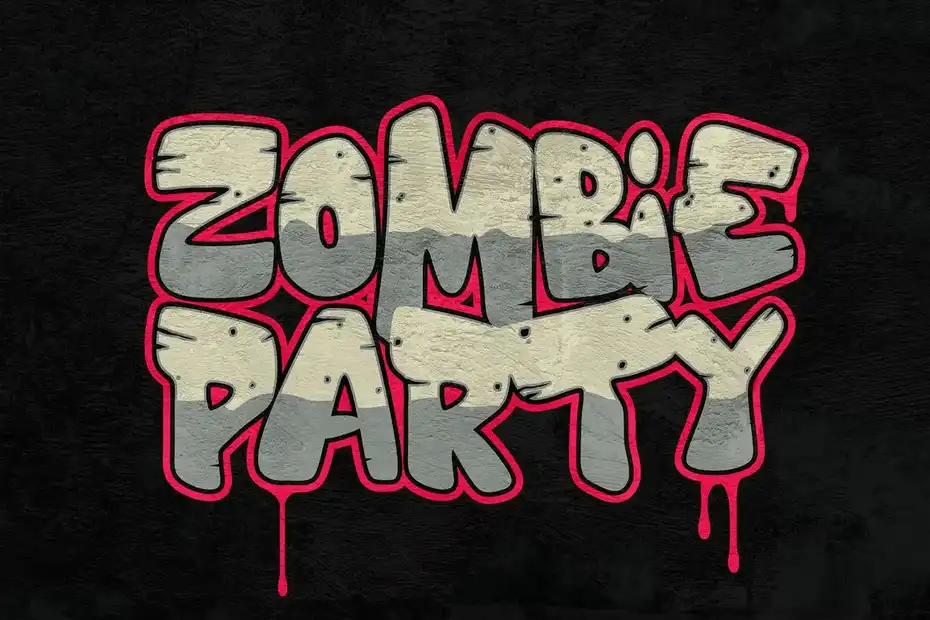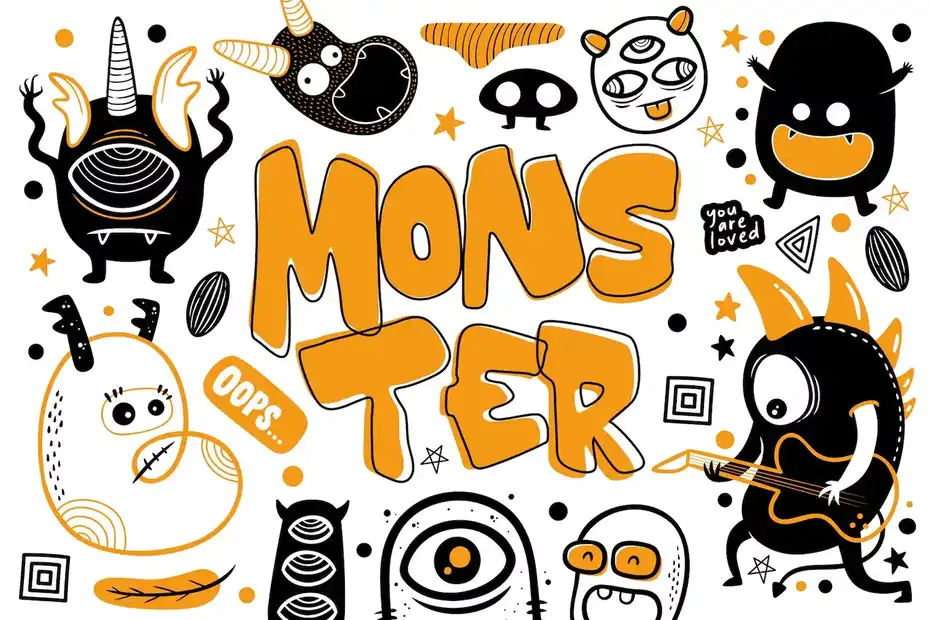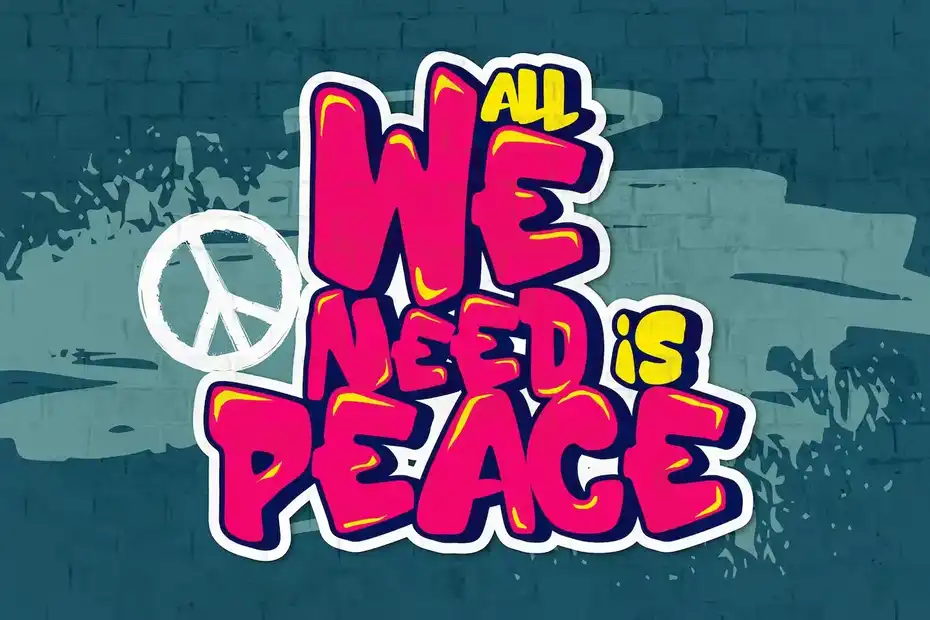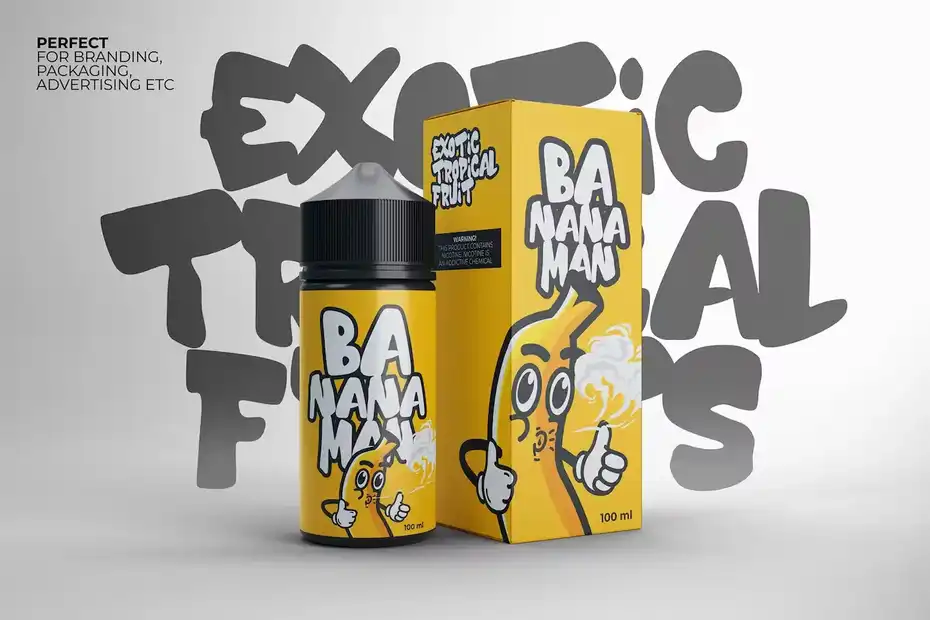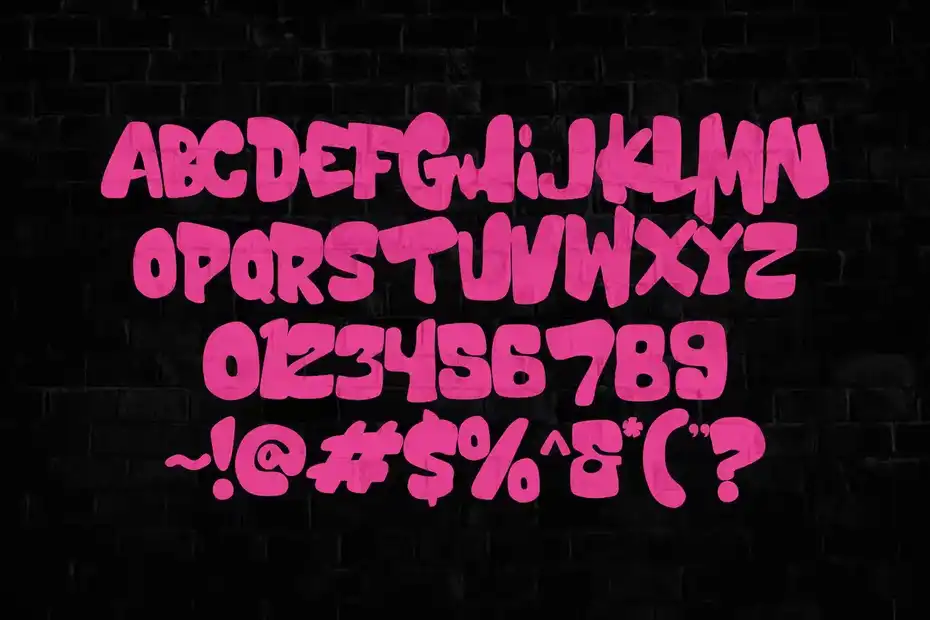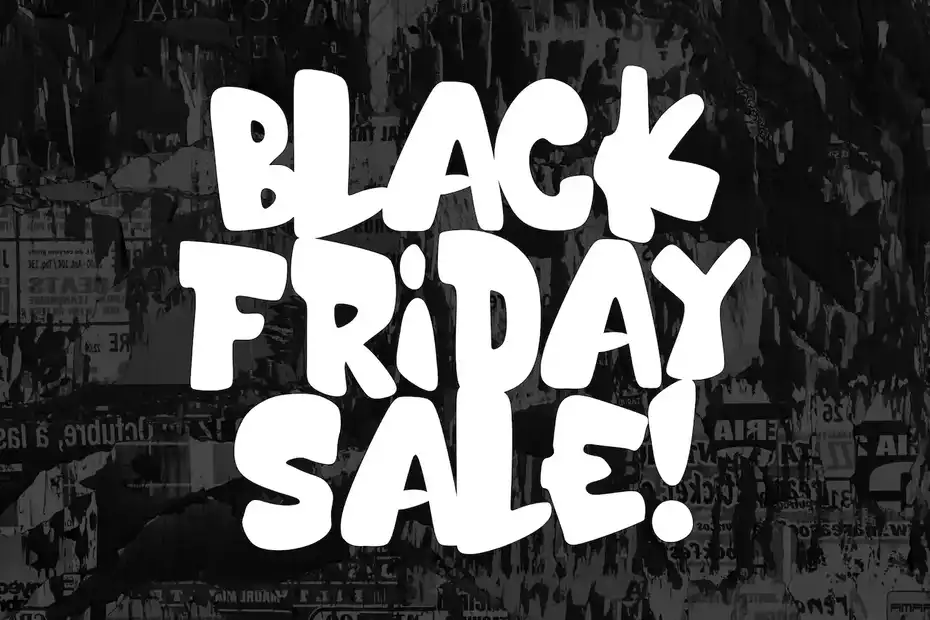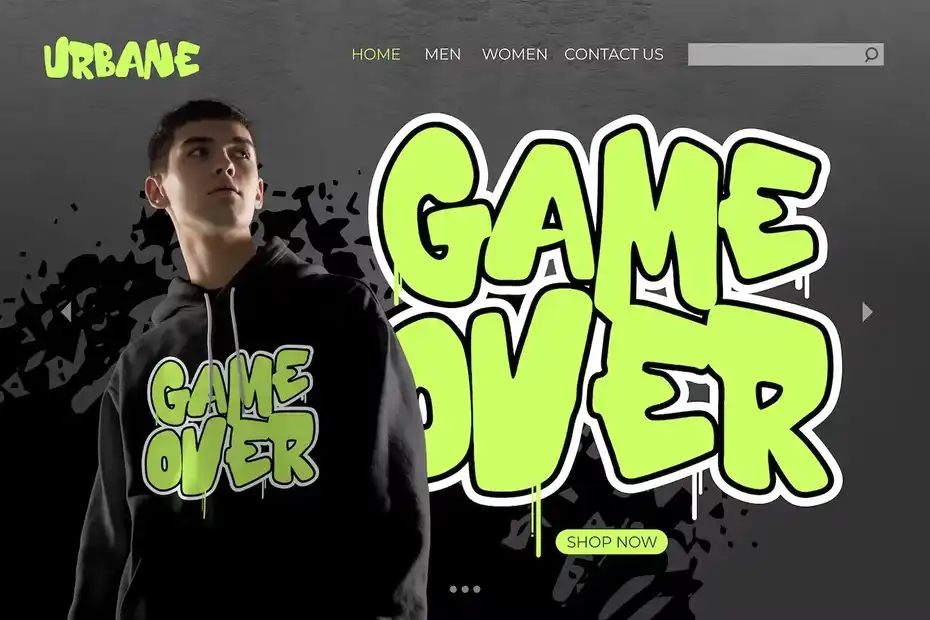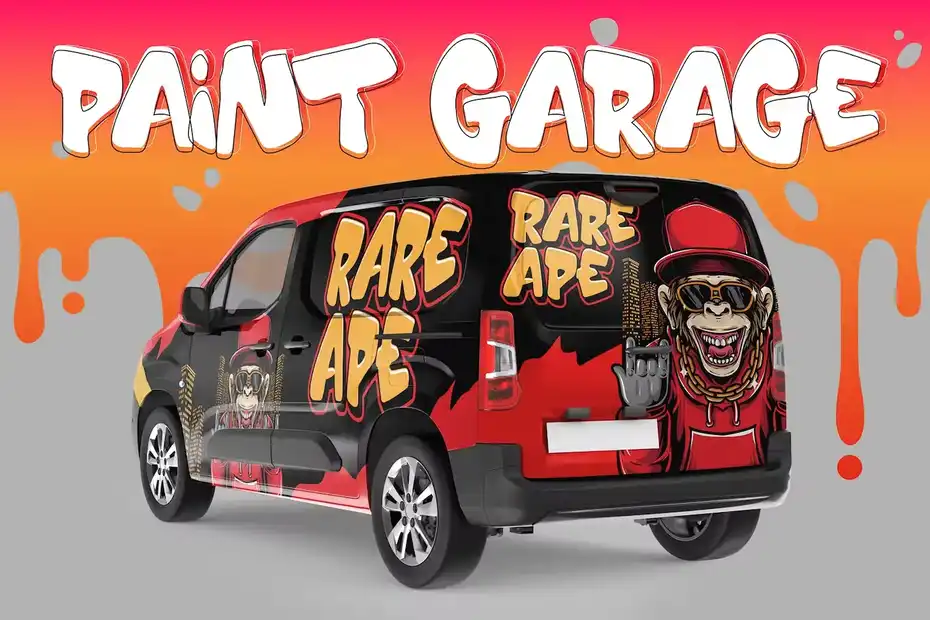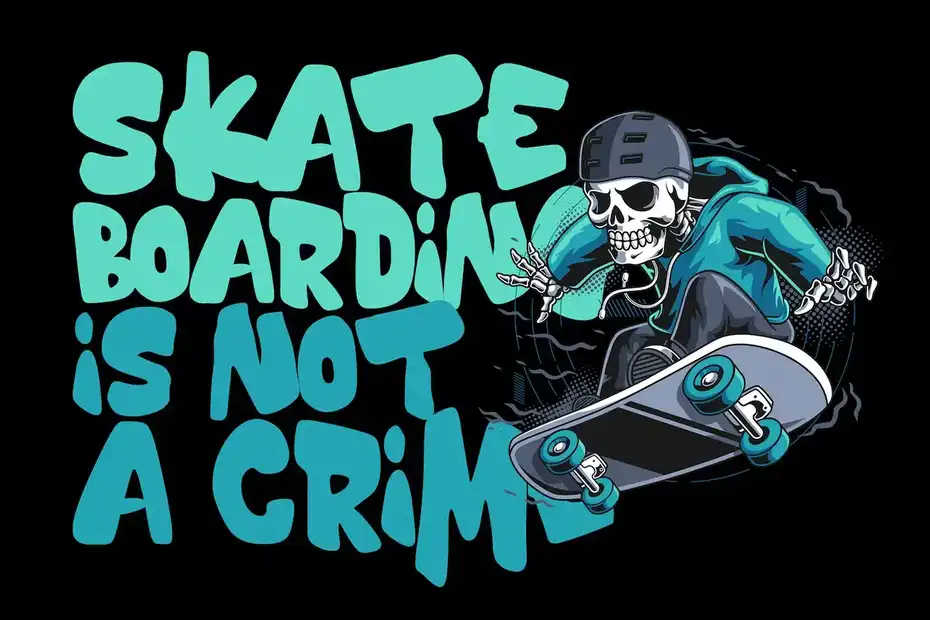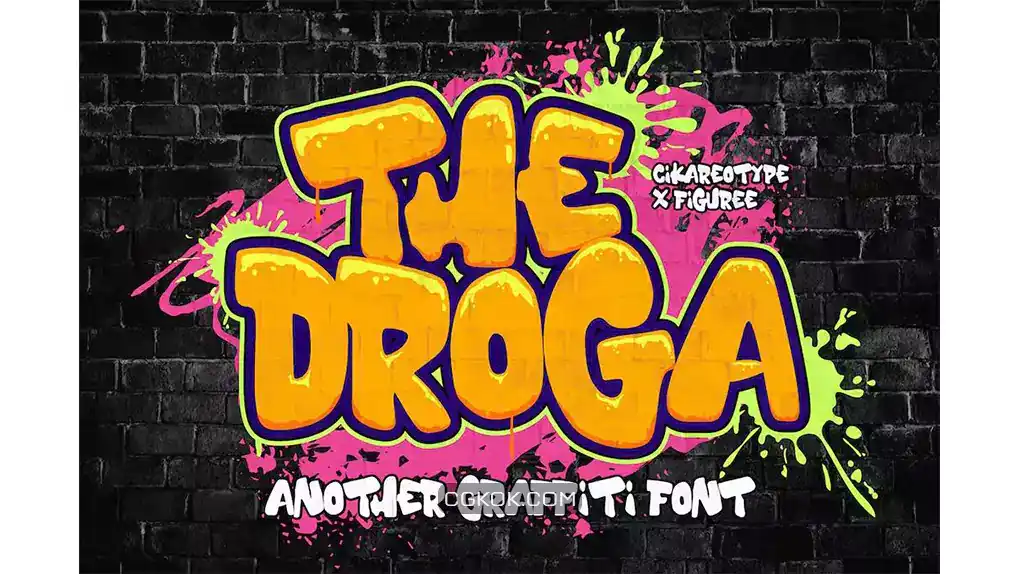
دانلود فونت گرافیتی ضخیم The Droga – Thick Graffiti Font
دانلود فونت گرافیتی ضخیم The Droga – Thick Graffiti Font : این مجموعه شامل یک فونت انگلیسی گرافیتی است که برای برندینگ، سربرگ، کارت عروسی، دعوت‌نامه‌، امضا، لوگو تایپ‌، تصاویر هنر دیواری، برچسب‌ و غیره مناسب میباشد.